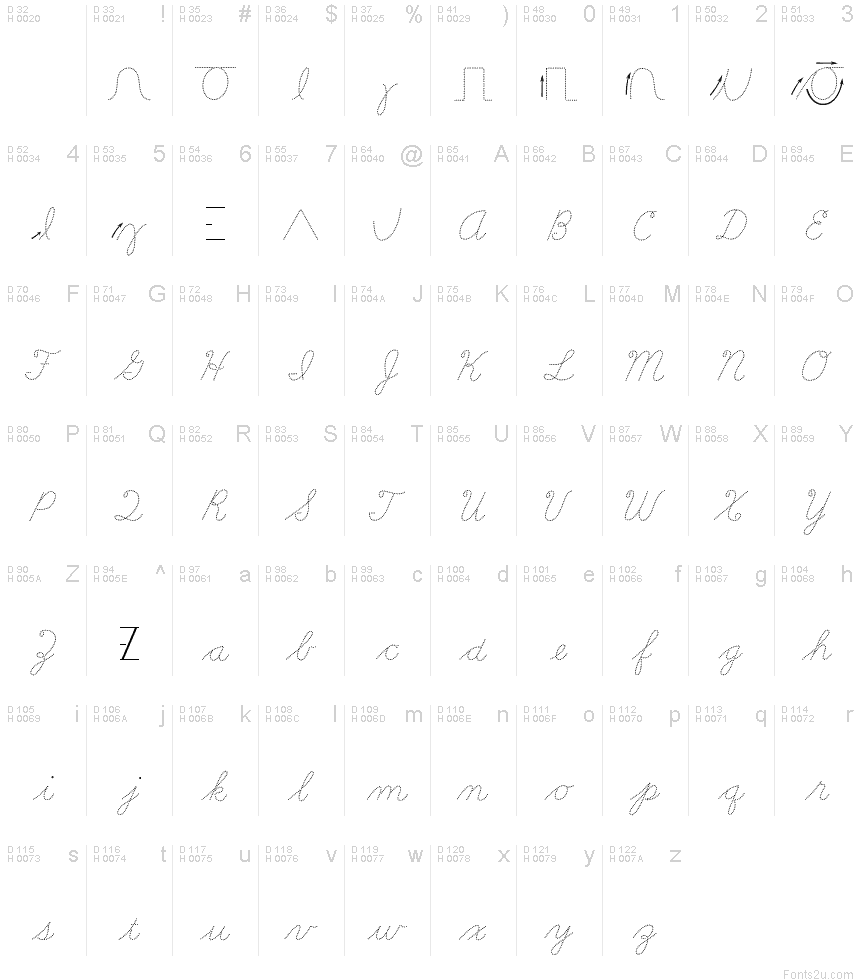
Learning Curve Dashed od Blue Vinyl Fonts je bezplatné školní písmo, které mění spojité ruční psaní na dráhu tvořenou rovnoměrně rozmístěnými tečkami. Tento rytmus tečkování připomíná procvičování krasopisu s dlouhými smyčkami a lehkým, vedeným pohybem, který zůstává v celém návrhu konzistentní.
Nejpřirozenějším využitím jsou školní pracovní listy, stránky pro nácvik psaní, výukové plakáty, kartičky a materiály pro domácí výuku. Tečkovaná konstrukce navíc dodává krátkým nadpisům na učitelských materiálech, tabulkách odměn a listech s aktivitami jasný instruktážní tón, který by běžné kurzívové písmo nevytvořilo.